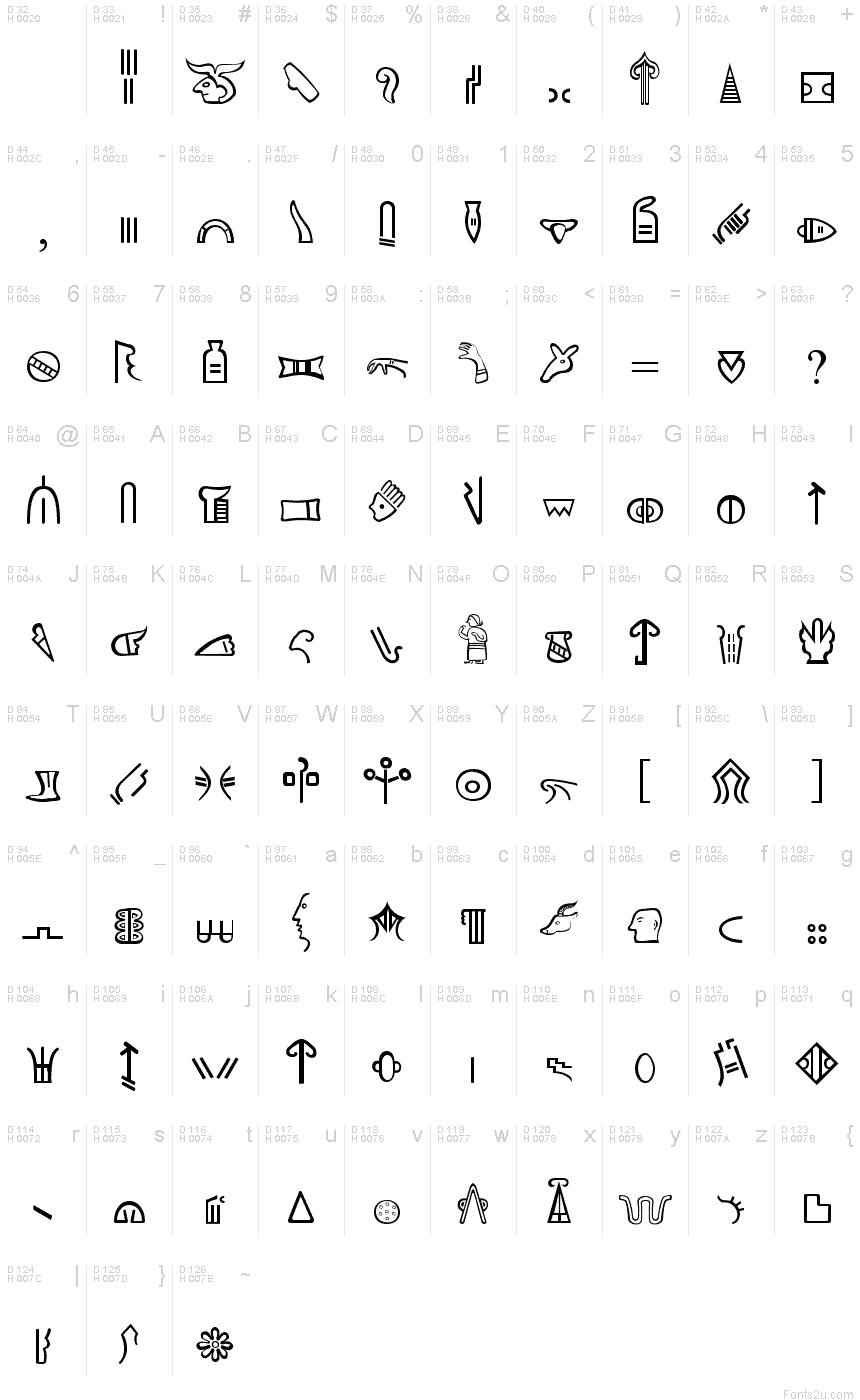
LUWHITTA od Guntera Anderse je bezplatné abstraktní dingbat písmo, které působí jako minimalistické značení a ručně kreslené symboly. Jednotlivé znaky kombinují zaoblenou geometrii, háčkovité tahy, rozdělené kruhy, šipky a úhlové emblémy, což celku dodává dynamický, zakódovaný vzhled, který připomíná spíše orientační systémy nebo notaci než pouhou dekoraci.
Toto bezplatné písmo se hodí pro projekty, které potřebují spíše symbolické akcenty než slova – plakáty, obaly desek, titulky, packaging, ziny nebo grafika rozhraní. Využijte ho pro oddělovače, ikonické prvky, nadpisy inspirované mapami nebo krátké brandingové momenty, kde tyto výrazné, zjednodušené tvary dokážou samy o sobě vytvořit směrovou, až kryptickou atmosféru.